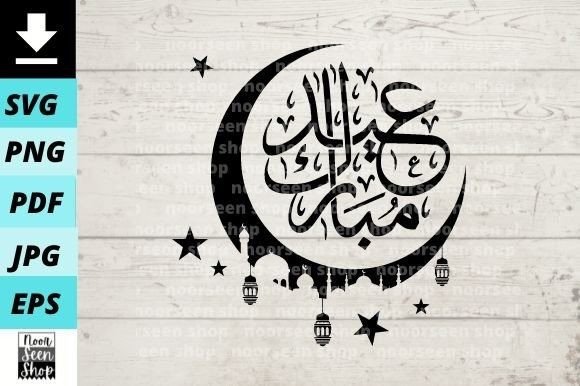
EID Mubarak
適切なデザイン要素を見つけるのは難しい場合がありますが、EID Mubarakは作品を即座に引き立てる優れたコレクションを提供します。
POD(オンデマンド印刷)製品、結婚式の招待状、またはソーシャルメディアのグラフィックを作成している場合でも、EID Mubarakは理想的です。